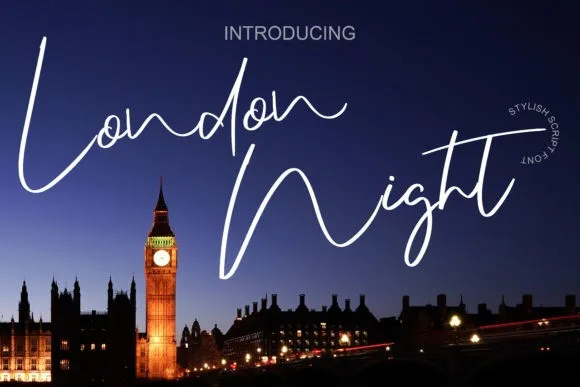
London Night Font – Fonte Grátis
London Night Font
A fonte London Night é uma elegante iluminura escrita a mão leve que adicionará um toque luxuoso a qualquer projeto de design que você deseja criar. Com seu charme único e impacto impressionante, esta fonte será perfeita para dar um toque sofisticado às suas criações digitais. É ideal para nomes de marca, gráficos de mídia social, embalagens ou qualquer outro elemento visual onde uma escrita elegante é desejada. Perfect for adding a touch of luxury and elegance to your digital projects, London Night font is the perfect choice for designers looking to elevate their work with a beautifully handwritten feel.